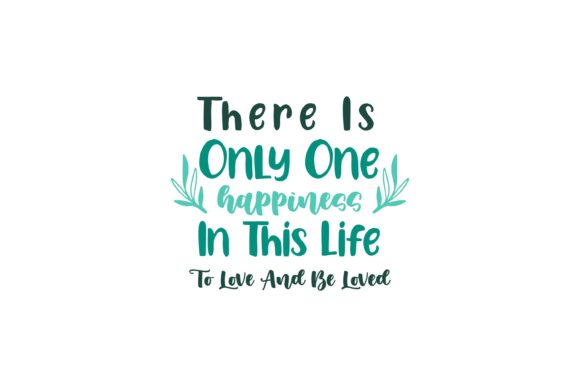
In This Life-Love Quotes Colors Font
การค้นหาองค์ประกอบการออกแบบที่เหมาะสมอาจเป็นเรื่องท้าทาย แต่ In This Life-Love Quotes Colors Font นำเสนอคอลเลกชันที่โดดเด่นซึ่งช่วยยกระดับงานของคุณได้ทันที
ไม่ว่าคุณจะสร้างผลิตภัณฑ์ POD (Print on Demand) คำเชิญงานแต่งงาน หรือกราฟิกโซเชียลมีเดีย In This Life-Love Quotes Colors Font ก็เหมาะสมอย่างยิ่ง